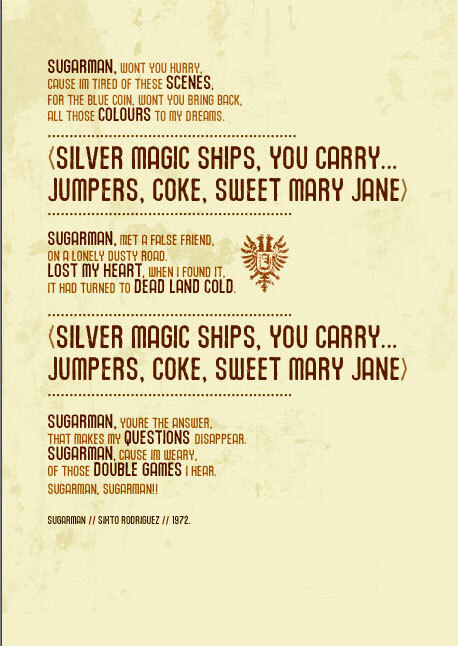
Union Agrochem Charkrapetch
Union Agrochem Charkrapetch di Polenimschaufenster prod. è un font display gratuito dallo stile eroso, caratterizzato da maiuscole alte e smussate e bordi irregolari e vissuti, che richiamano le scritte delle vecchie fabbriche. Le lettere sono strette e solide, ma le tacche e i bordi graffiati fanno sì che non appaiano troppo rigide o rifinite.
È perfetta per poster, packaging, flyer musicali, titoli e progetti di branding che cercano un'estetica industriale e usurata, senza sfociare nel vintage script. Essendo un font gratuito, dà il meglio di sé in righe brevi, testi di copertina e wordmark audaci, dove quelle maiuscole "segnate" colpiscono subito nel segno.